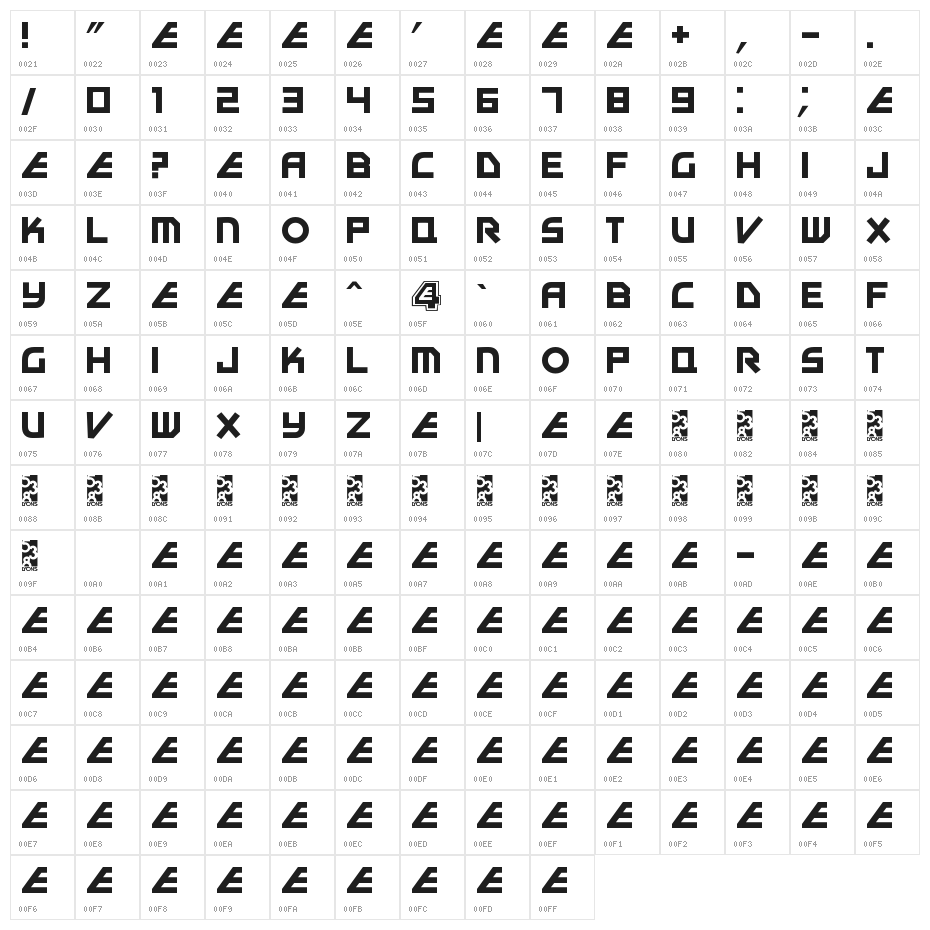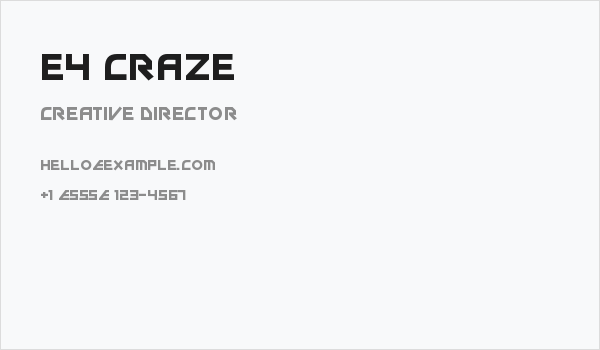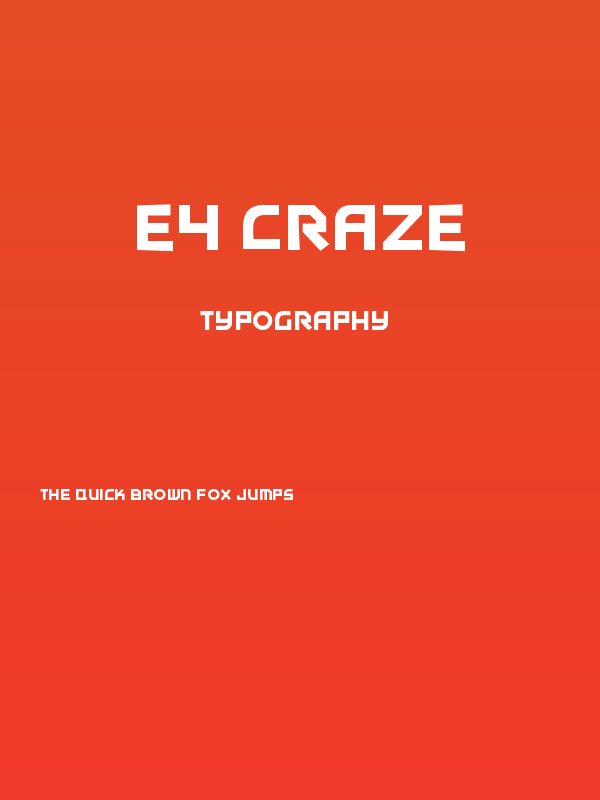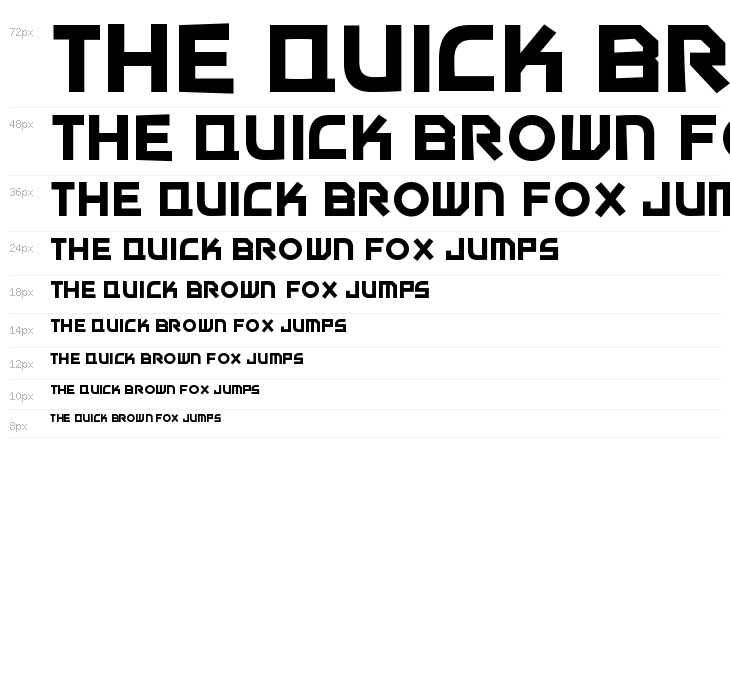
E4 Craze Font
✎ Futuristic
| Vorgeschlagene Projekte | Ideal for technology branding, sci-fi themed projects, video game titles, and modern advertising campaigns. |